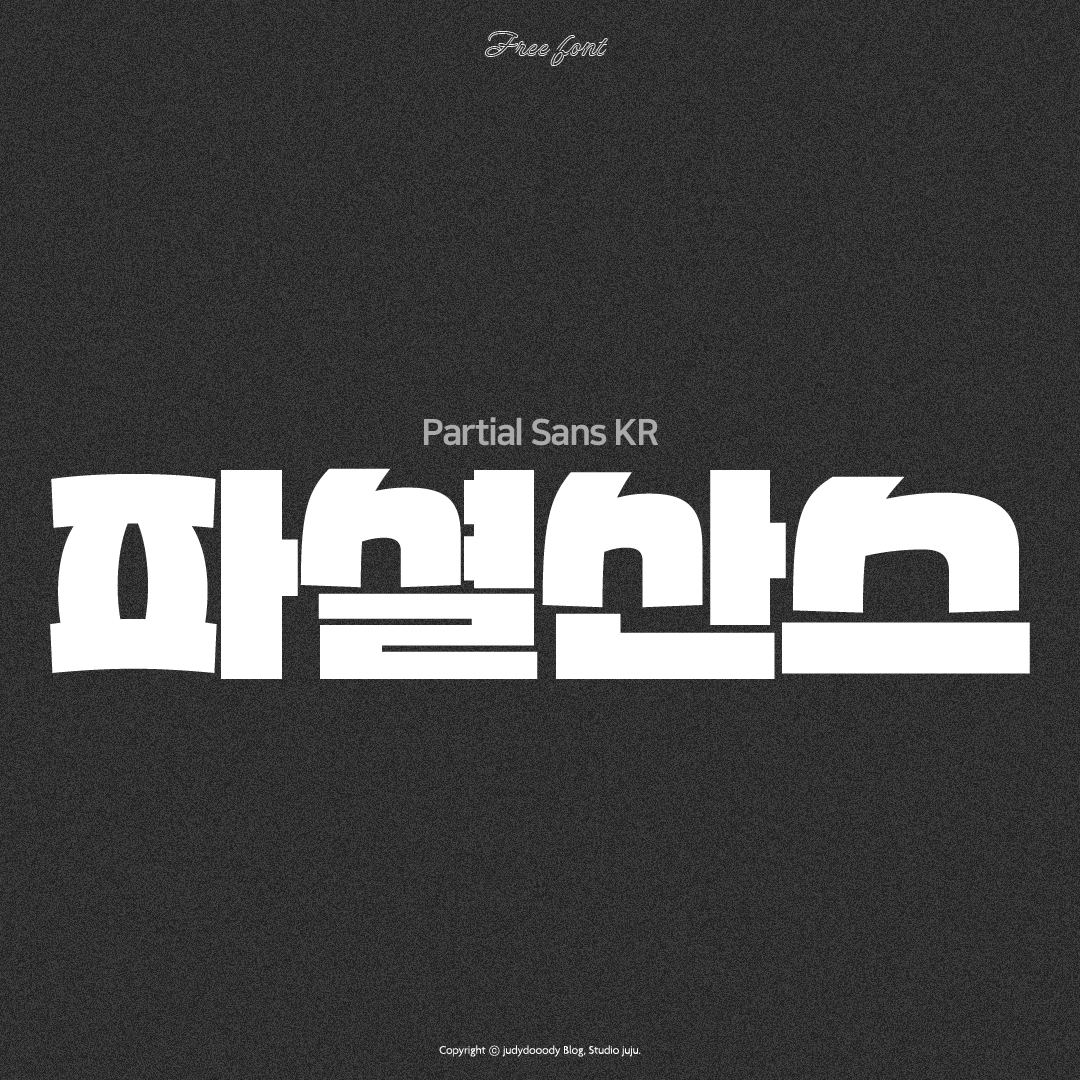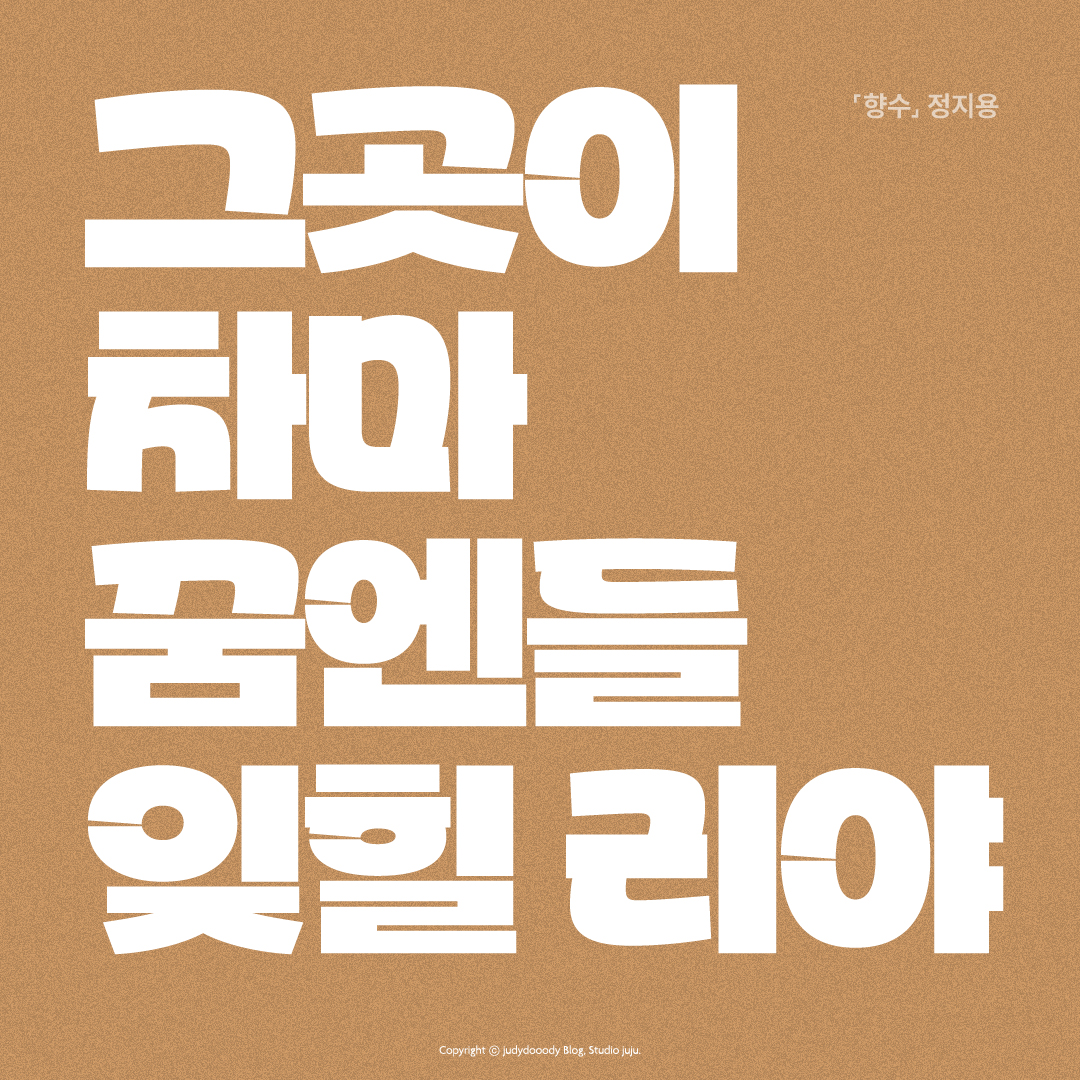
요즘 정말 잘쓰고 있는 폰트 중 하나인데요.
부드러움과 딱딱함을 모두 가지고 있어 여기저기 활용하기 좋더라구요.
파셜산스체는
Partial 파셜의 '부분적인, 편애하는'이라는 단어에서
영감을 받아 제작되었다고 합니다.
중성과 종성의 디자인은 스탠다드하고 직선적인 디자인인데,
그에 반해 초성은 곡선을 활용하고 동글한 인상이라
딱딱해보이지 않고 귀여운 느낌을 전달하는 서체입니다.
폰트 카테고리
산세리프 San serif
고딕체 아주 굵은 서체
강조용, 제목용 서체
박준영(@typejjun__)
폰트 사용 예시
매우 두꺼운 고딕서체이다보니,
레트로한 감성에도 잘 어울리고 강조하는 부분에도 잘 어울립니다.
제목 서체로 포인트를 주어도 좋습니다.